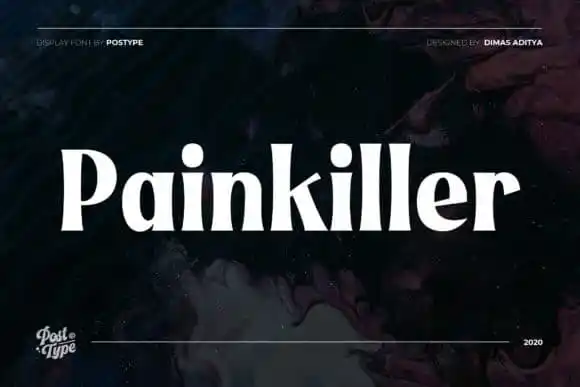
A fonte Painkiller Display é uma elegante escolha para qualquer projeto que precise de destaque visual. Postype a criou com precisão e originalidade, oferecendo um design clean e único. Esta letra robusta e poderosa combina perfeitamente para eventos, como festas de casamento ou grandes eventos corporativos. Seja uma camiseta personalizada, um logotipo, cartões de presente, stickers ou qualquer outro projeto criativo – Painkiller Display está aqui para revitalizar suas ideias únicas. Suave e delicada nas fontes de corpo, mas poderosa e impressionante como letras grossas, a Painkiller Display oferece uma experiência de trabalho completa e envolvente em seu próximo design visual.